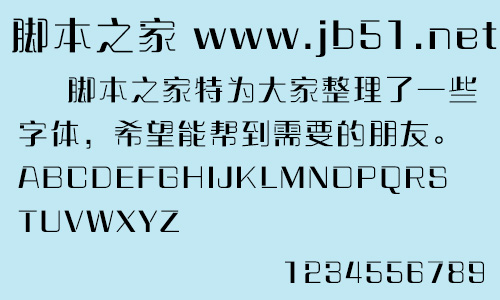
方正晴朗體簡(jiǎn)DemiBold是一款由方正字庫(kù)開(kāi)發(fā)的一款中文藝術(shù)字體,晴朗體普遍每一個(gè)字只有兩直劃是粗的,其余橫直都是細(xì)的,左邊上下直角,右邊上下是圓角,形成一個(gè)強(qiáng)烈對(duì)比,所以粗細(xì)的視覺(jué)很平均,適合應(yīng)用于藝術(shù)設(shè)計(jì)、平面宣傳設(shè)計(jì)、網(wǎng)頁(yè)設(shè)計(jì)、書(shū)法字帖等領(lǐng)域,需要的朋友可以前來(lái)本站下載。